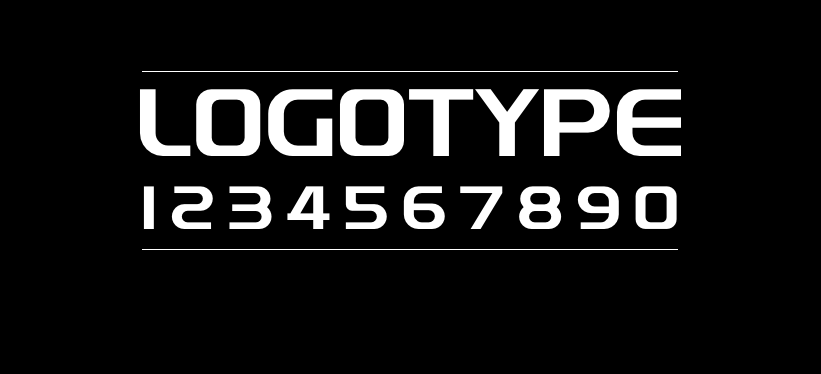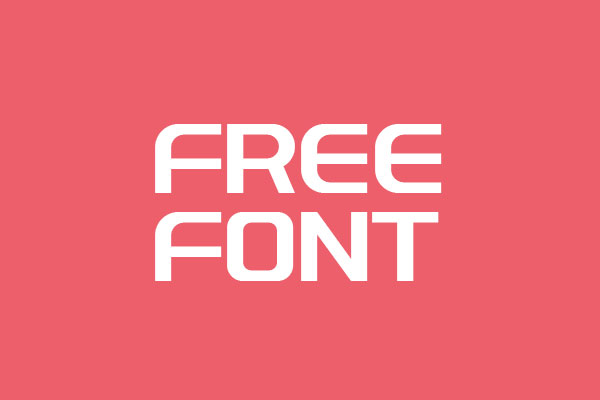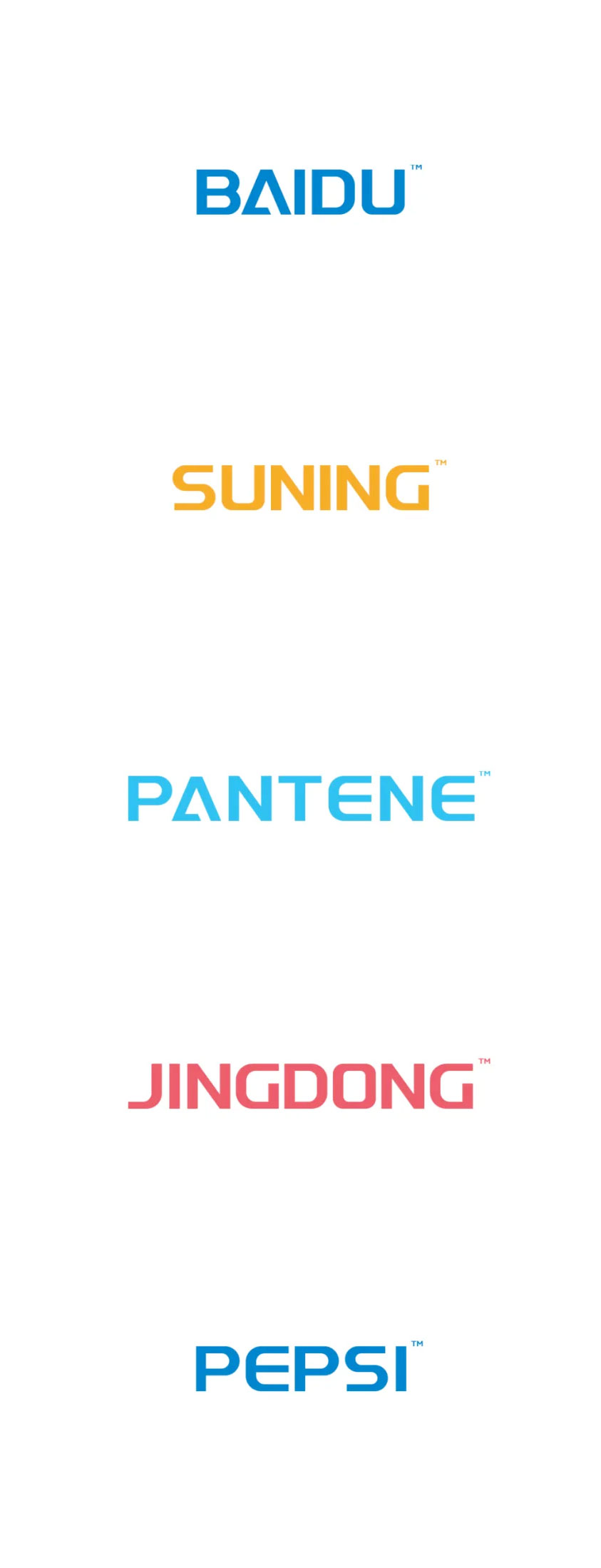
字体圈欣意LOGO体
字体圈欣意LOGO体是国内字体设计师邹乐伟创作的一套英文字库,适用于标题、LOGO设计等场合使用,目前包含52个英文10个数字和几个标点。
该字体无论是互联网公司,还是服装品牌,还是玩具公司,还是食品公司,还是大型企业等等,都是很适合的!
这套字巧妙之处在于,如果你的公司需要设计LOGO,但你不会做LOGO设计,你可以把字打出来,调个间距,调个颜色,国际化立马飙升!